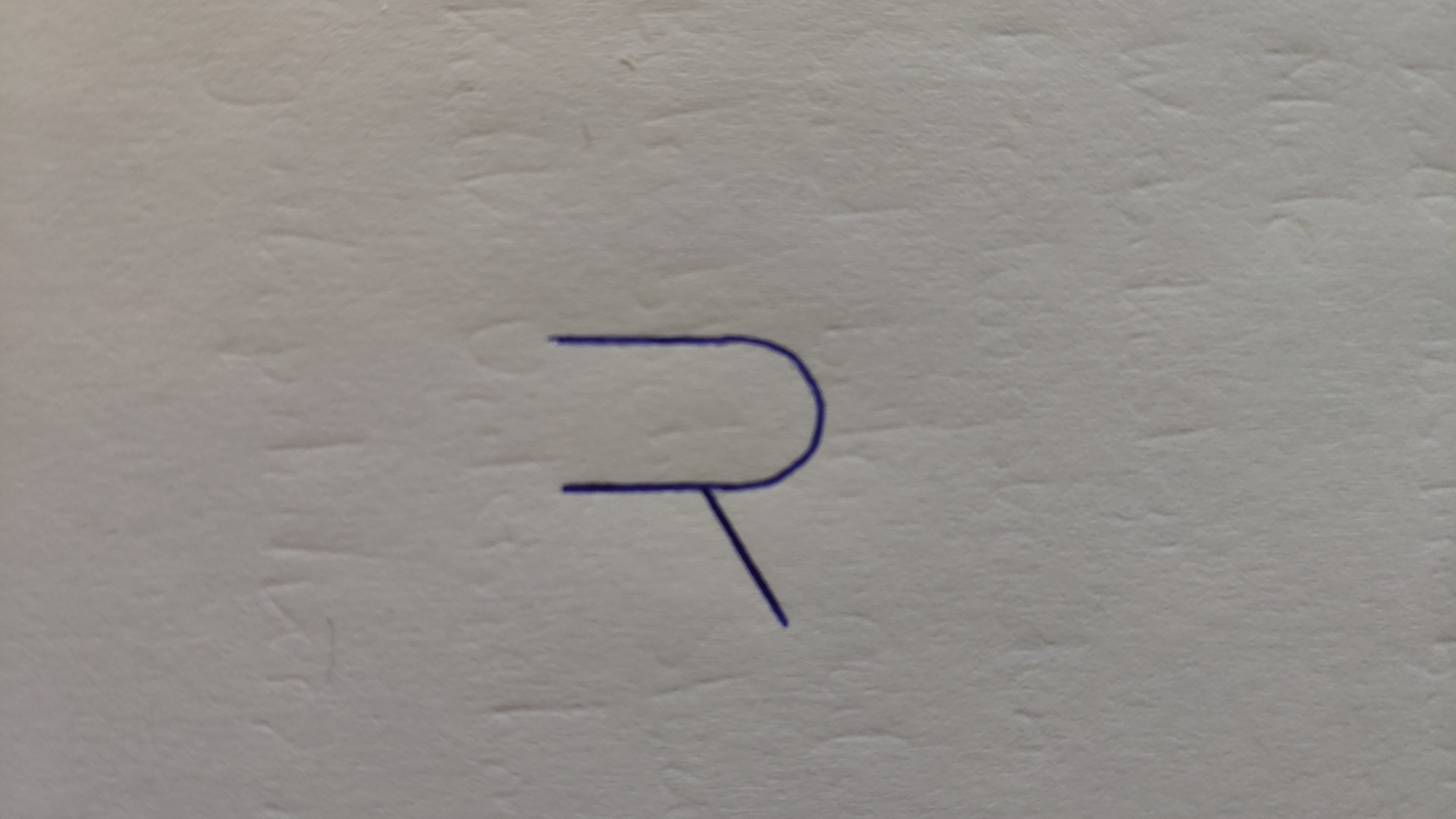
Schriftart ermitteln
Und zwar geht es um folgendes: Ich habe hier ein Dokument vor mir liegen. Auf diesem befinden sich verschiedene Texte in unterschiedlichen Schriften. Bei einer davon ist das "R" wie folgt geschrieben:
Ich bin nun auf der Suche nach Schriftarten (muss nicht Word sein), bei denen dieses "R" gleich bzw. in den hauptsächlichen Merkmalen ähnlich sieht. Da ich das Dokument leider nicht fotografieren und veröffentlichen darf habe ich den Buchstaben mal fachmännisch nachgezeichnet. Die Proportionen sind wie gesagt nicht entscheidend, es geht lediglich um das äußere Erscheinungsbild.
Anhand eines Buchstabens kann man keine Font ermitteln, aber wenn du mehr davon hast, kannst du o.g. Tool verwenden.
Vielen Dank für den Link. Leider ist auf dem Dokument nur dieses "R" so markant.